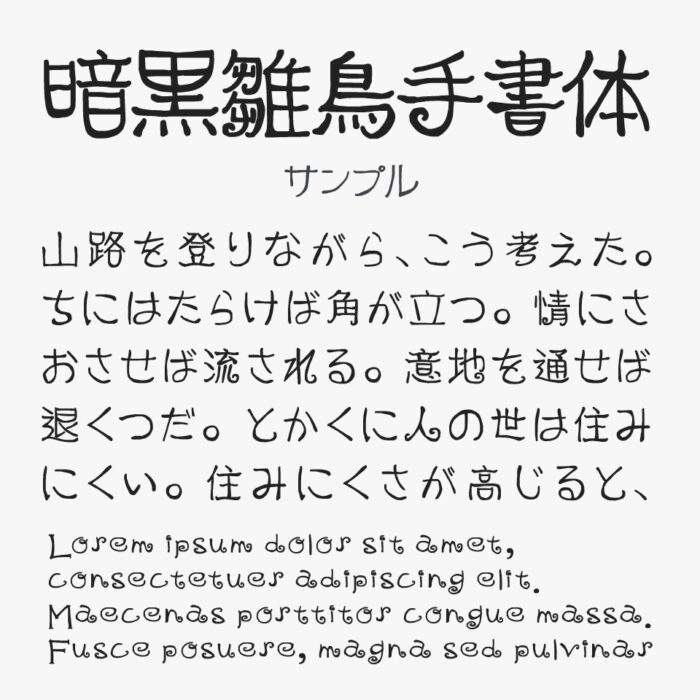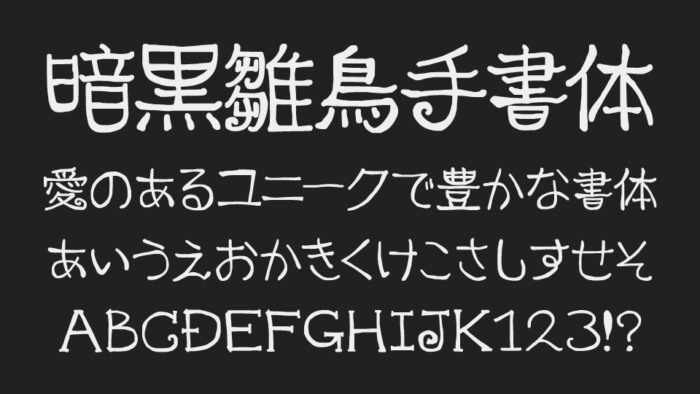
暗黒雛鳥手書体フォントは、クルっと遊び心のあるユニークでちょっとクセのある線が特徴的な手書きフォントです。
インクで書いた文字がそのまま紙に残ったかのような滲み感、線の太さに抑揚がありリアルな揺らぎを感じるのが魅力の手書き文字です。
文字の一部がクルっとなっていて、どこか遊び心も感じさせてくれるファンタジー感のあるフォントとなっています。